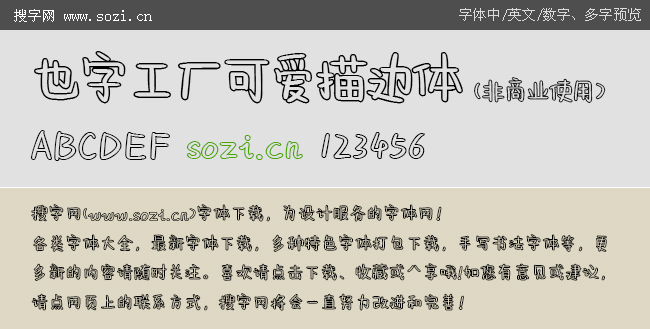
也字工廠可愛描邊體
搜字網(wǎng)給大家提供一款也字工廠可愛描邊體(非商業(yè)使用)中文字體下載,也字工廠可愛描邊體是一款卡通字體,字體是可愛的書寫風(fēng)格,并做成了鏤空的描邊效果,非常可愛有趣。具有很好的視覺效果。適合應(yīng)用于兒童繪本、兒童海報(bào)、網(wǎng)頁設(shè)計(jì)等應(yīng)用(此字體為個(gè)人非商用版,商用可以聯(lián)系:官方網(wǎng)址:https://yefont.com/home,聯(lián)系方式:13798980448)。